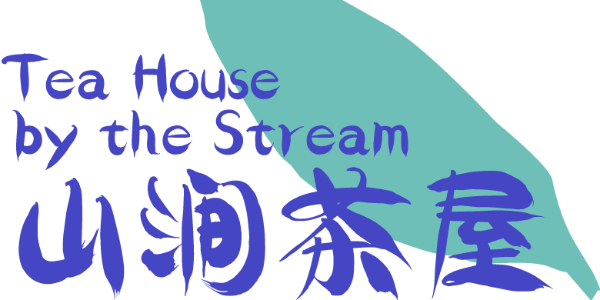
以字体传达青春的力量
汉仪小松致青春由汉仪字库签约设计师孙小松书写。字形饱满充盈,洋溢着青春气息,笔画流畅而随性,流露出年轻活力。这款字体如同一篇为青春书写的赞歌,也如同一行为美好记忆书写的注脚,不管是应用于青春题材的动漫影视,还是毕业旅行的vlog,都能以文字传达青春的力量。
字形中部饱满充盈,上下两端微收。
笔画圆起而尖收,粗细变化有弹性,书写流畅而随性。
笔画之间轻轻的连带和笔画末端的明快的回勾,如同青春匆匆。
西文部分以同样轻松随性的笔画书写,流露出青春的气息。